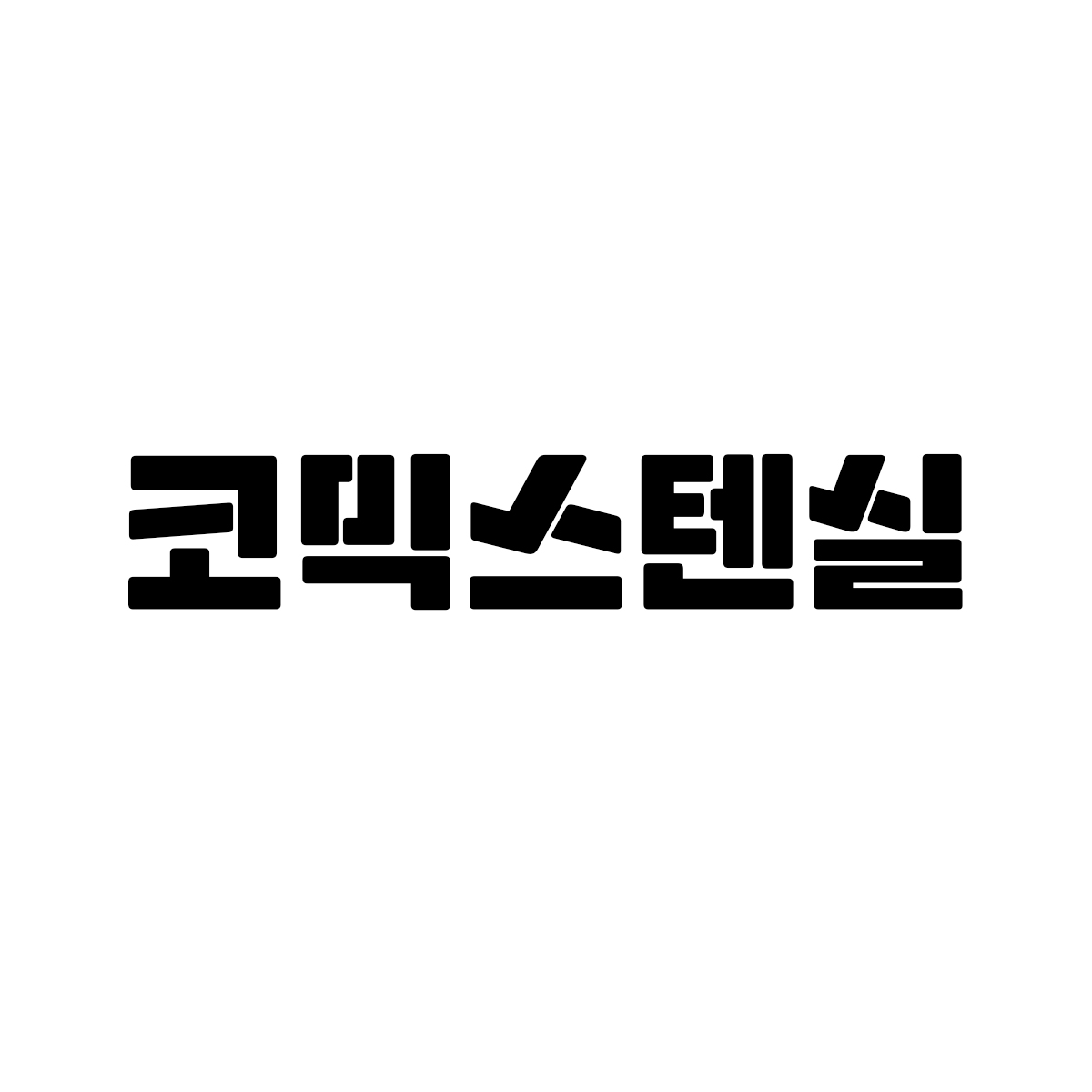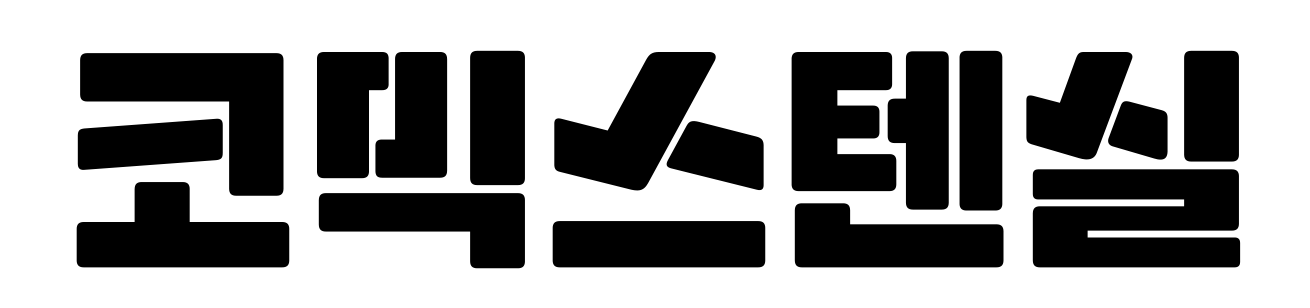
Sandoll 코믹스텐실
산돌 코믹스텐실은 자소를 오려내 공간을 채우는 스텐실 기법을 적용한 산돌의 세 번째 스텐실 폰트다.
꽉 찬 모듈과 ㅅ, ㅈ, ㅊ의 달리는 듯한 형태로 디자인 된 획의 특징들이 에너지 넘치고 즐거운 느낌을 준다. 또한 Shadow 패밀리를 사용하면 따로 효과를 주지 않아도 유쾌한 임팩트를 전달할 수 있다.
엉뚱하고 액티브 한 이미지를 연출하거나 임팩트가 필요할 때, 방송자막이나 헤드라인용으로 사용하면 좋다.
또한 Adobe-KR-9 규격이 적용되어 기존에 표현하지 못했던 뷁, 똠얌꿍 같은 표현들이 가능해졌다.